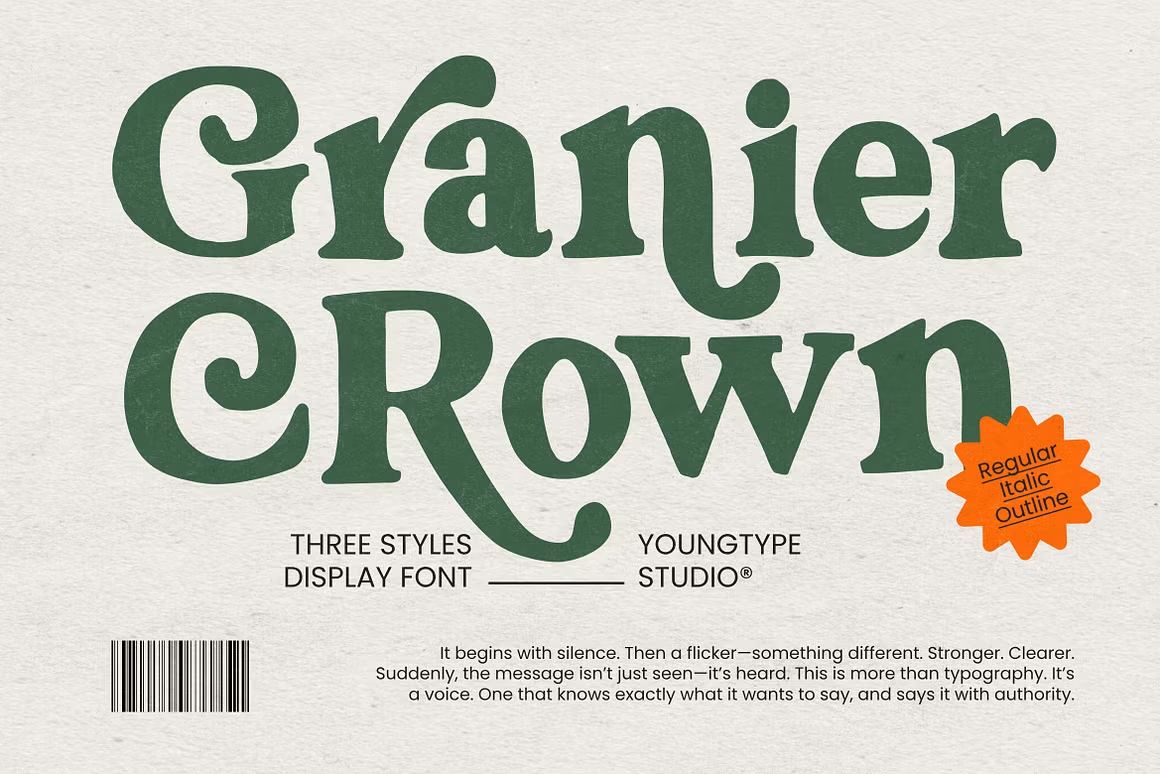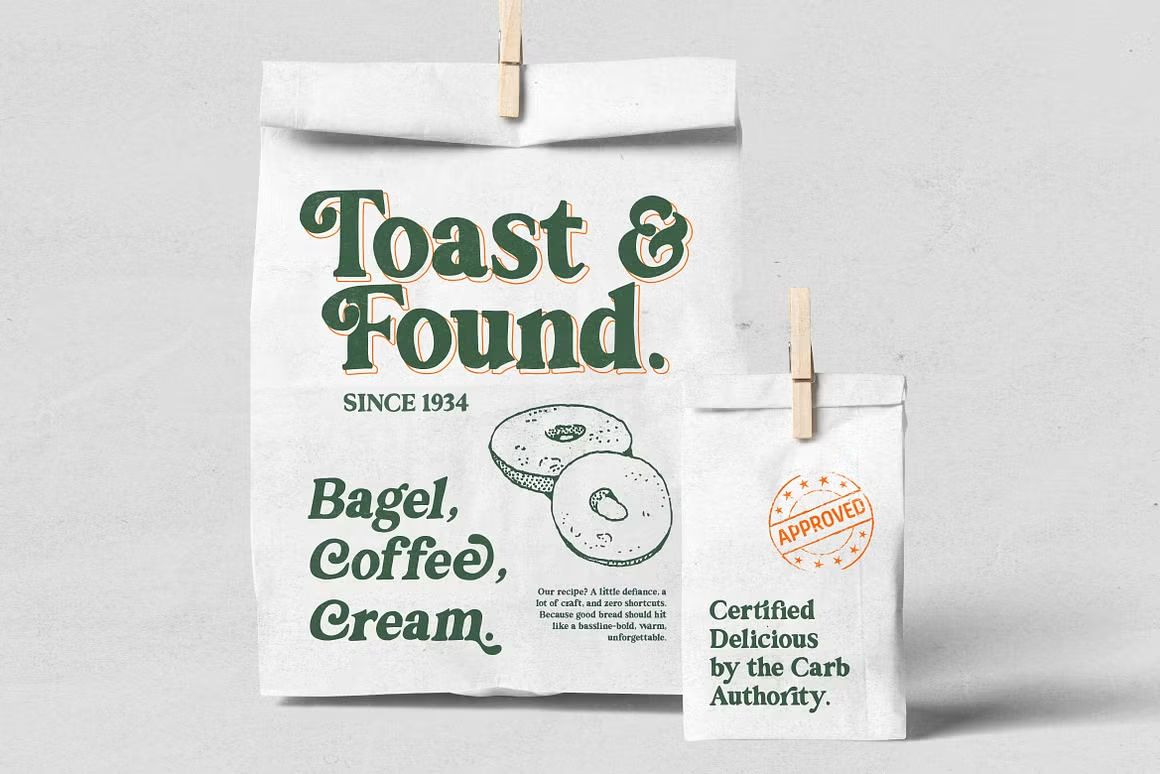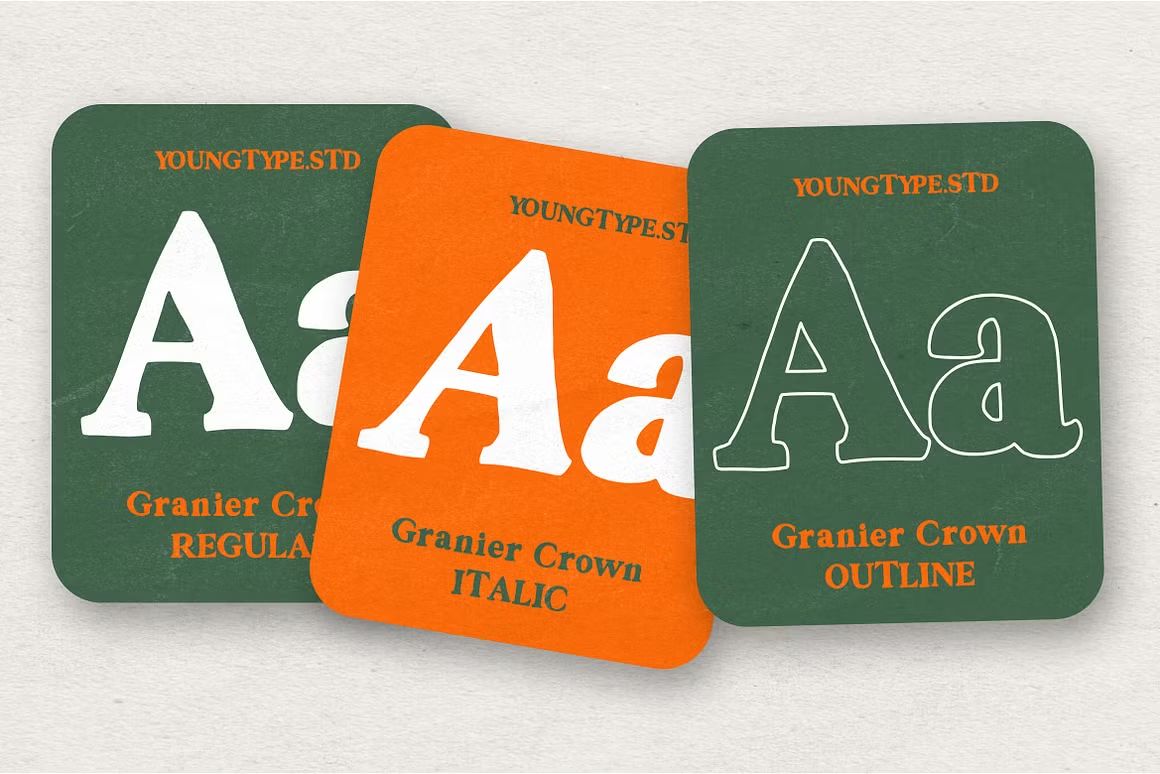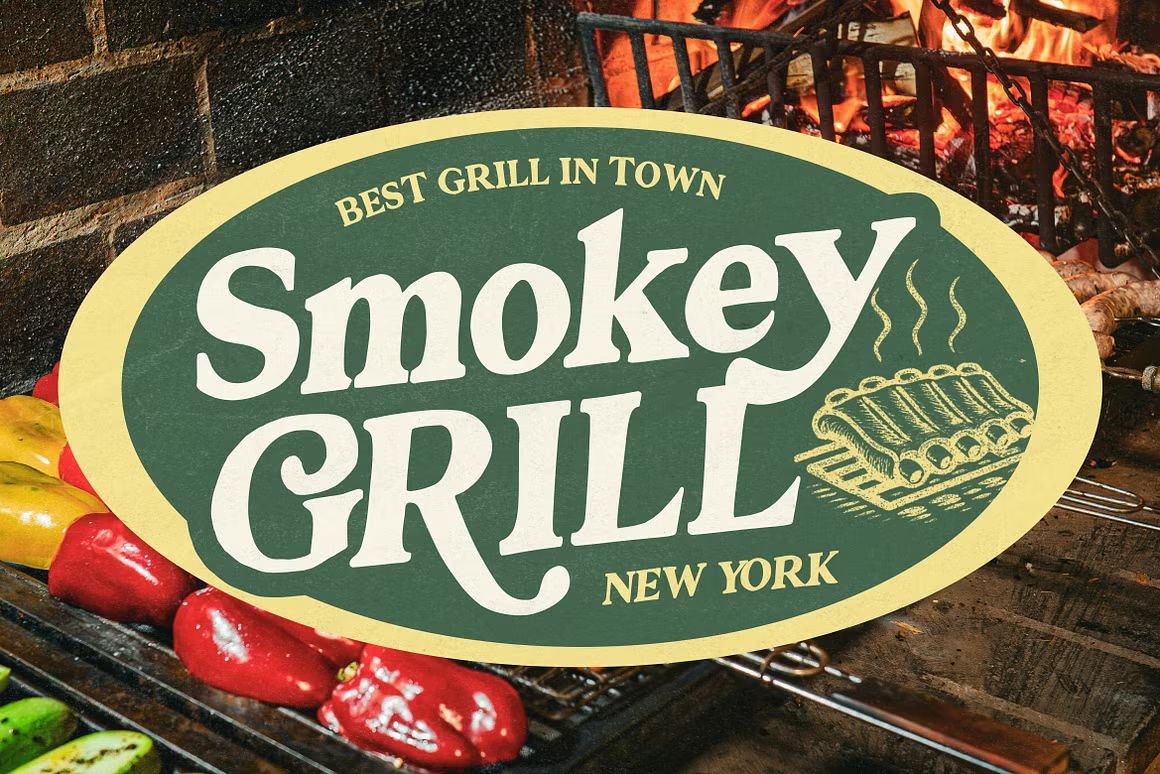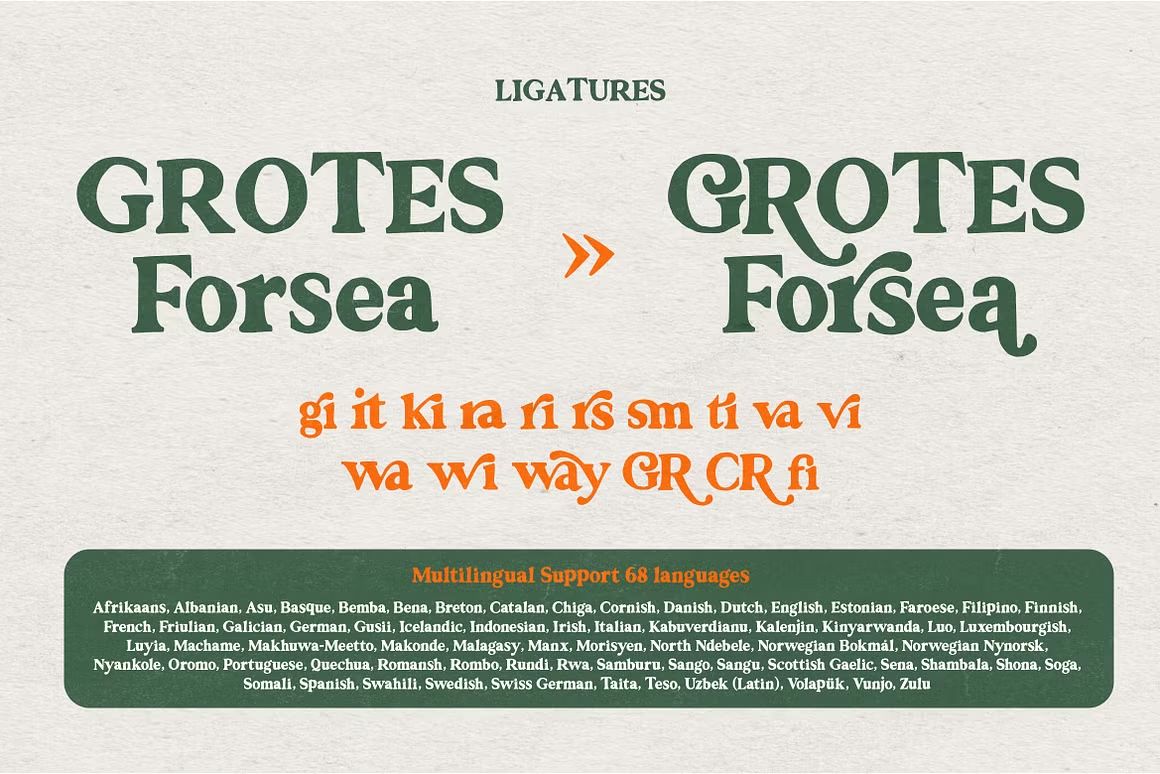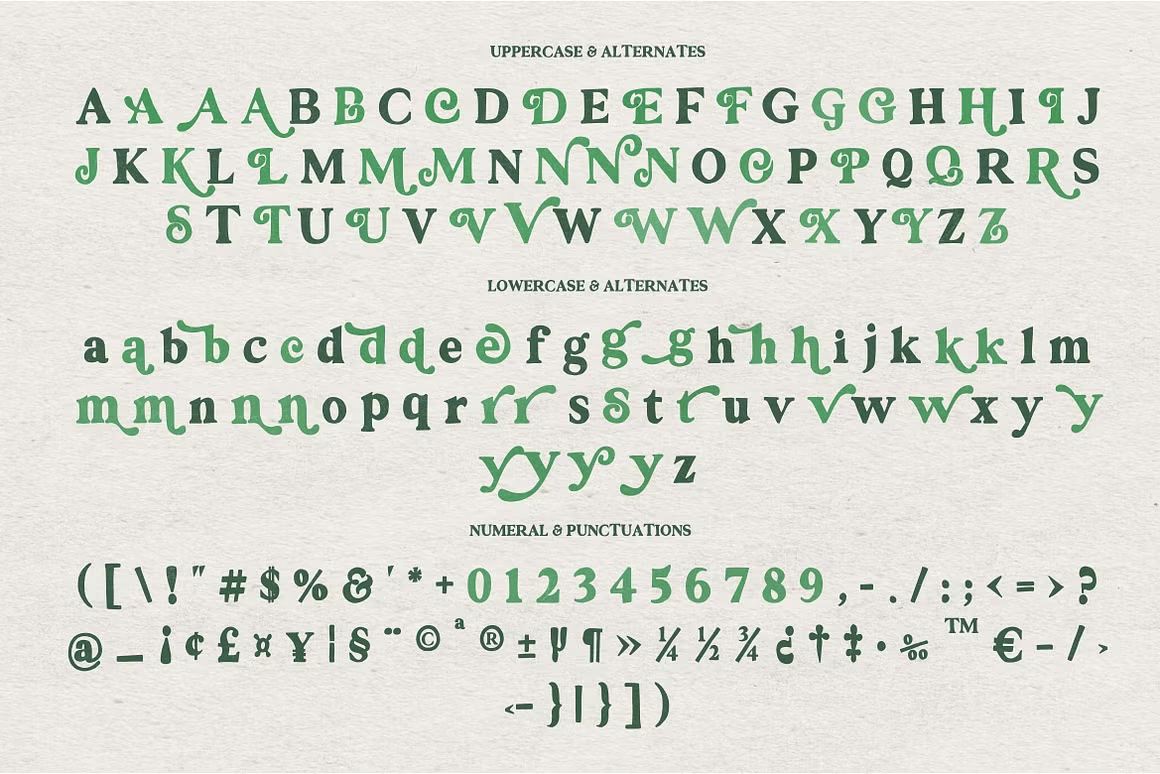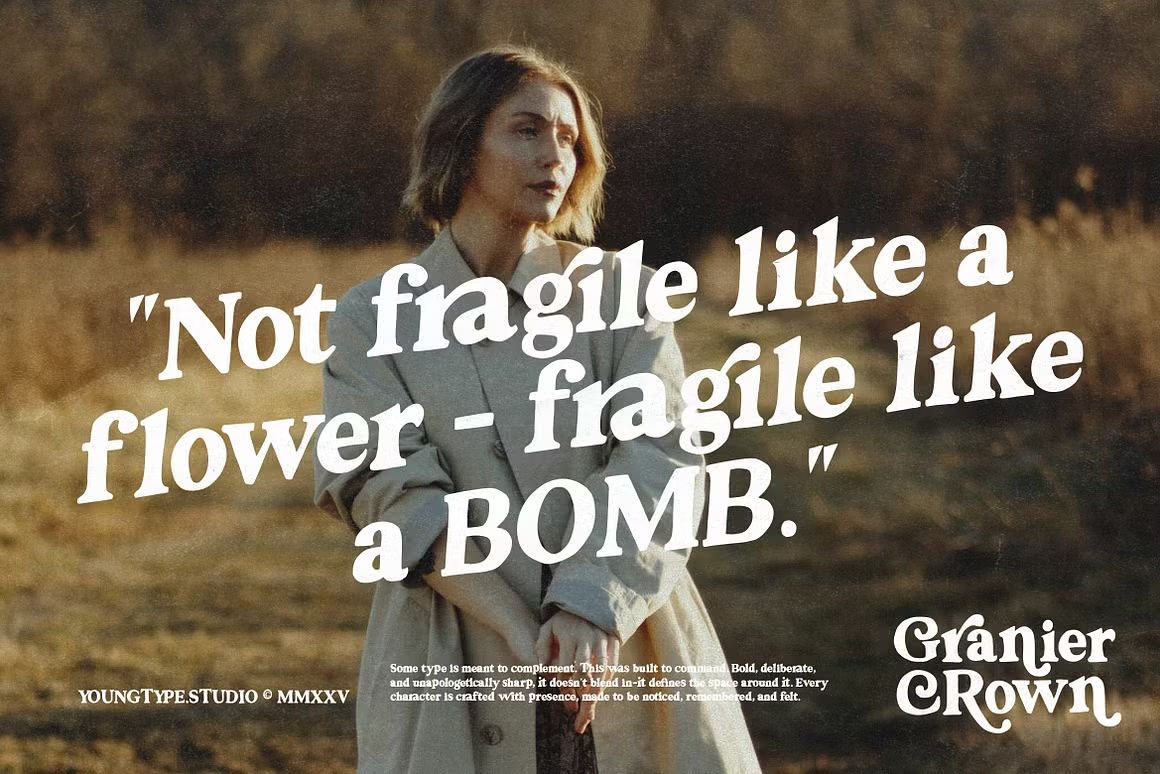
Granier Crown – Handwritten Font
Granier Crown adalah font handwritten dengan gaya modern dan elegan, menampilkan goresan yang halus dan ritme tulisan tangan yang mengalir. Font ini sangat cocok untuk proyek desain seperti branding personal, undangan pernikahan, logo, kemasan produk, dan kutipan estetik. Dengan tampilan yang anggun namun tetap santai, Granier Crown menghadirkan nuansa eksklusif dan hangat dalam setiap desain.
• Gaya tulisan tangan halus & elegan
• Termasuk huruf besar, kecil, angka, simbol, dan ligatur